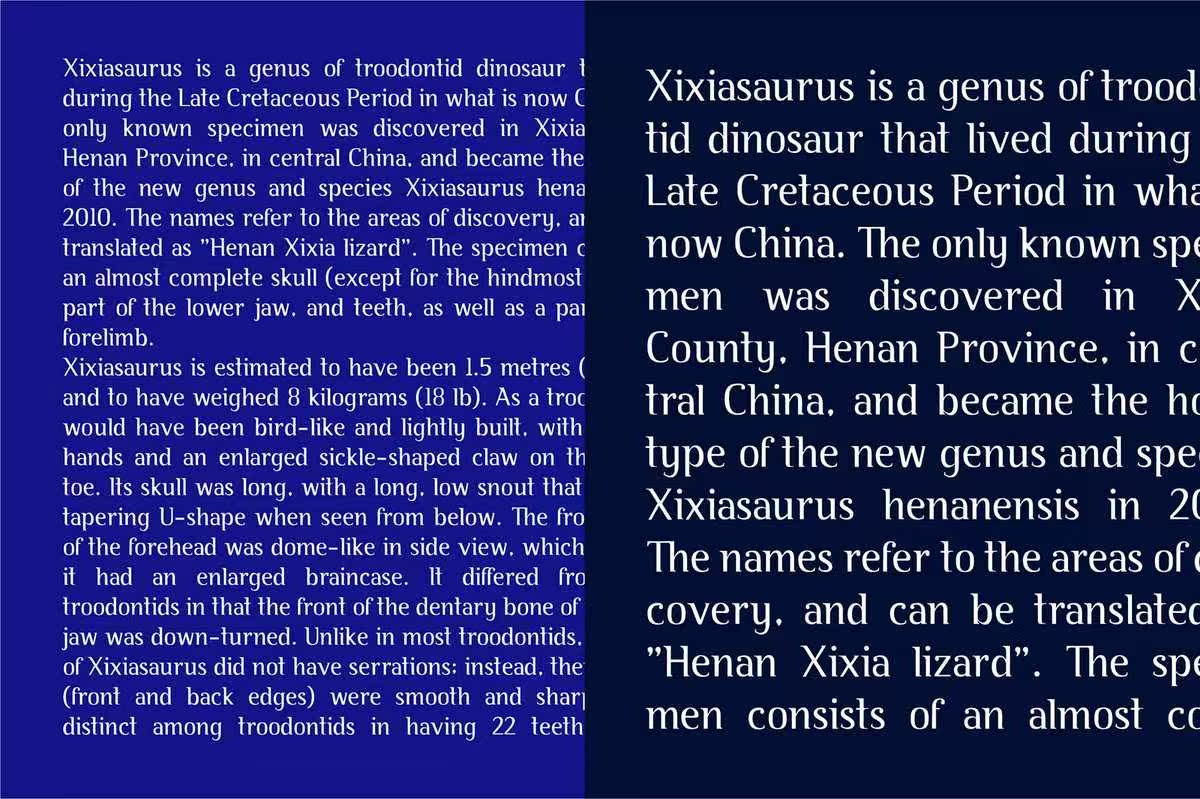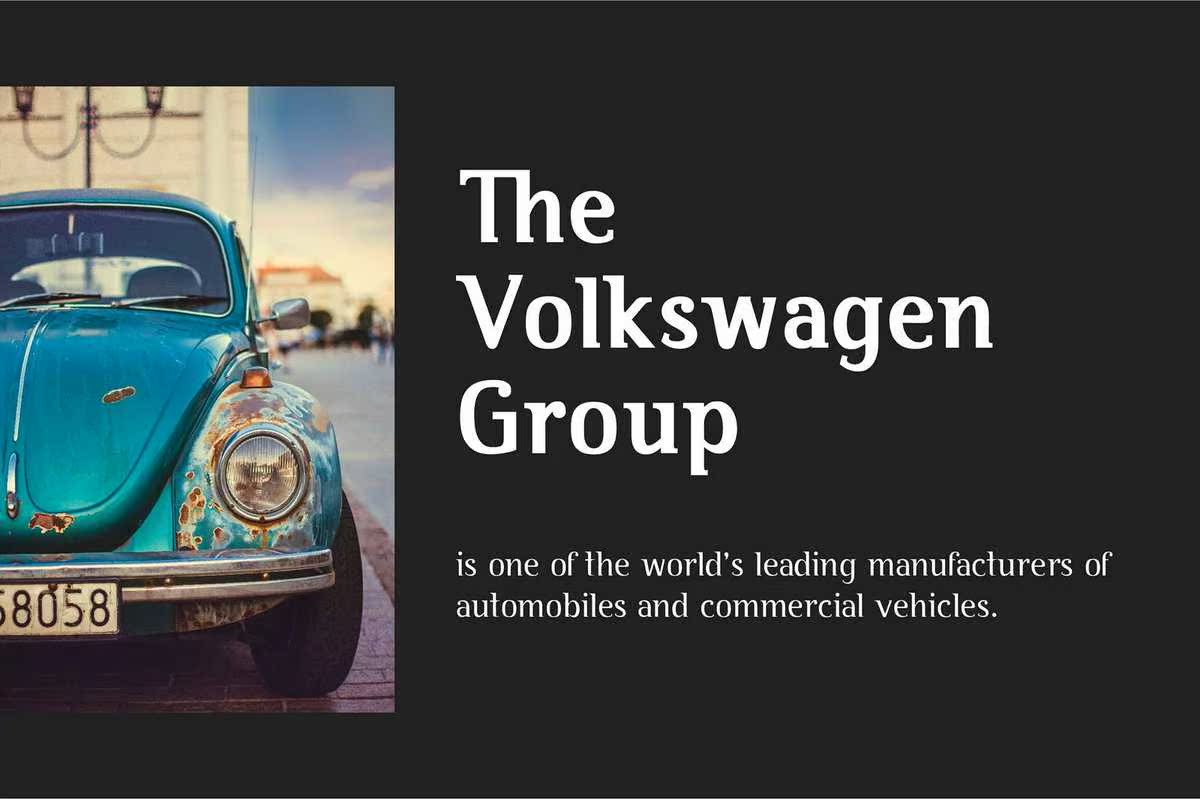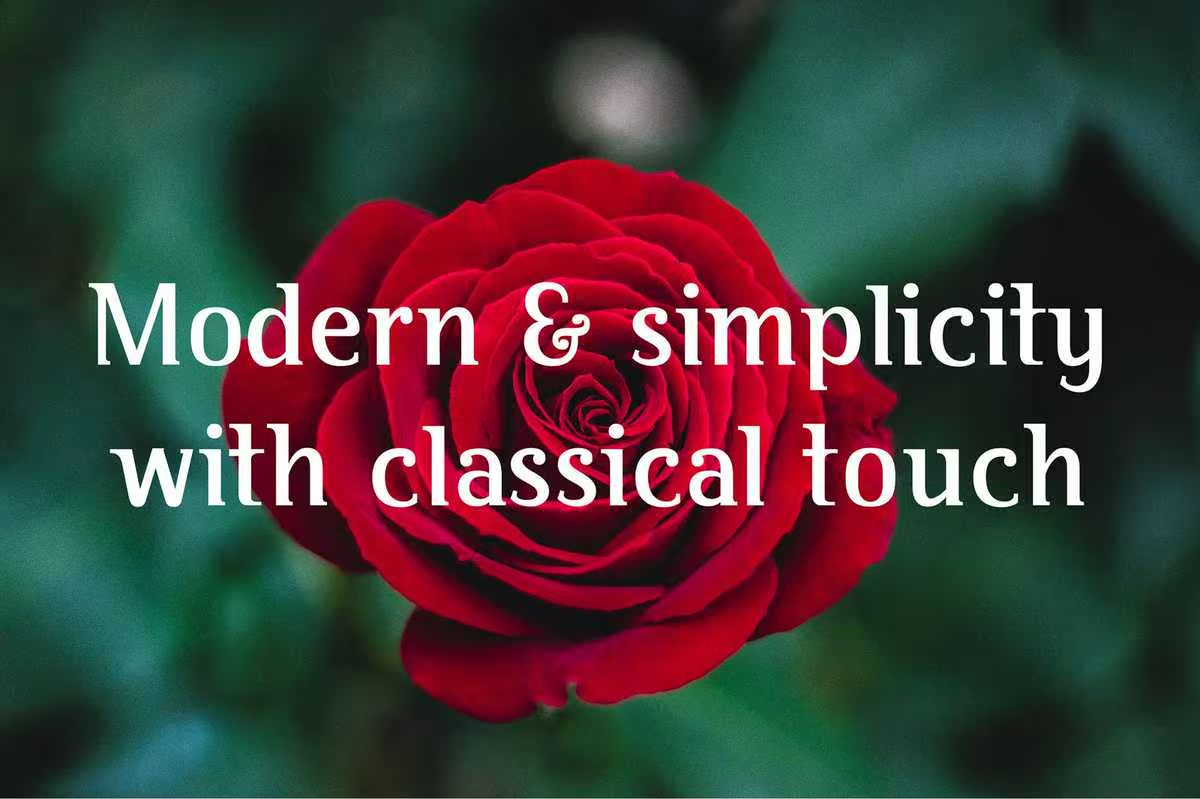
Sajidahisa Modern Classic Serifont.Sajidahisa Font具有现代风格,可用于在不丢失ERIF经典内容的情况下进行女性和现代印刷。Sajidahisa有三种不同的字体,分别为常规、半粗体和粗体。此字体可用于标题、正文、,和标识。SajidahisaModernClassificalSerifont。SajidahisaFont具有现代风格,可用于在不丢失ERIF经典内容的情况下进行高级和现代印刷。SajidahisaFont有三种不同的字体,分别为普通、半粗和粗体。该字体可用于标题、正文和标识。